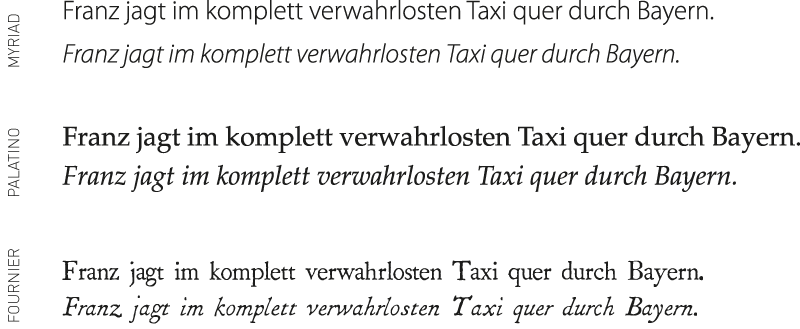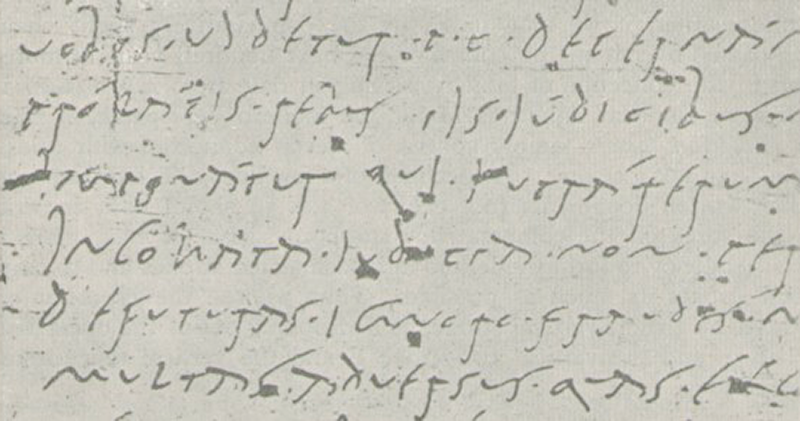
Die Bezeichnung „Kursive“ stammt aus dem Lateinischem ‚currere‘ = laufen, rennen und steht für schräg – meist nach rechts geneigte – laufende Schrift.
Die Geschichte der Typografie hängt unmittelbar zusammen mit der handgeschriebenen Schrift und Kalligrafie.
Die Form der Glyphen und der Duktus der Schrift – die sich aus der Form der Spitze des Schreibwerkzeugs und seiner Führung mit der Hand ergeben haben – haben später auch Einfluß auf die Form und das Aussehen der geschnitzten, gegossenen bzw. gedruckten Schrift. Während die Majuskeln (Großbuchstaben) von den römischen Inschriften (Antikes Rom, Trajanssäule) und die Minuskeln (Kleinbuchstaben, Gemeine) aus den Kleinbuchstaben des altgriechischen und römischen Alphabets abegeleitet werden, ist die Kursive eine Nachahmung der handgeschriebenen Schrift.
Die zahlreichen Abschriften der Majuskel-Schriften (Capitalis) führten zur Entstehung einer Majuskelkurssive (Capitalis Cursiva). Durch die ständige Veränderung der Form der Buchstaben entwickelte sich schliesslich die Minuskel mit den langen Endungen und Schleifen oben und unten (daher die Bezeichnung der Drei-Zonen-Schrift der „jüngeren römischen Kursive“).
Die Ausbreitung des Frankenreiches des Kaisers Karl des Großen führte zur Entstehung der „karolingischen Minuskel“ in der geraden und kursiven Ausprägung. Die Blütezeit erlebte die humanistische kursive Minuskel in der Renaissance. Sie setzte sich aus den Kleinbuchstaben der karolingischen Minuskel und den Großbuchstaben der Capitalis monumentalis. Einer der größten Förderer der humanistischen Minuskel war Niccoló Niccoli (1363–1437).
Die humanistische Minuskel war die Vorläuferin einer flüssig geschriebenen kursiven Form, welche ebenfalls unter dem Einfluß von Kalligraphen zur gepflegten Cancellaresca führte. Von der Mitte des 15. Jahrhunderts an entstanden in der päpstlichen Kanzlei die Sendeschreiben in vollendeter humanistischer Kursive, der Cancellaresca corsiva (oder littera da brevi) und der Cancellaresca formata, wogegen die päpstlichen Erlässe weiterhin in der littera da bolle, einer gebrochenen Schrift, geschrieben wurden. Die Cancellaresca verbreitete sich in Kürze über Europa und wurde zur beliebten Handschrift von Gelehrten und Künstlern (Caflisch M., Schriftanalysen, Bd. 1, 2003: 50).
Direkt aus der Cancellaresca formata entwickelt Francesco Griffo aus Bologna im Auftrag des venezianischen Druckers Aldus Manutius um 1501 eine aldinische Kursive mit der die Klassiker im Taschenbuchformat gedruckt werden sollen. Das Exklusiv-Recht für den alleinigen Gebrauch der Kursive, das Manutius von der Stadt erhalten hat, ist wirkungslos geblieben – binnen kürzester Zeit verbreitet sich diese Form in ganz Europa. In den Jahren 1524–27 bekommt die aldinische Kursive neue Konkurrenz: die römische Kursive von Ludovico degli Arrighi (Ludovico Vincentino).
Die Kursive existierte ursprünglich als eigenständige Schrift, bis sie ab dem 17. Jahrhundert als eine „Ergänzungsschrift“ der Antiqua-Schrift geschnitten wird. Der Franzose Philippe Grandjean legt der Schrift „Romains du Roi“ im Jahr 1702 eine Kursive bei. Später folgten dem Trend der königlichen Druckerei auch Pierre Simon Fournier (der ergänzt die kursiven Minuskeln um Serife) und Firmin Didot.
Anwendung der Kursive
Die Kursive wird im deutschsprachigen Raum für Auszeichnungen im Text eingesetzt.
Sie wird häufig für kurze Zitate oder Audrücke in fremder Sprache verwendet. Der Einsatz der Kursivschrift in den Versalien oder für den Titel sollte gut überlegt sein und hängt oft von der Schrift ab. Die Kursive verändert den Grauwert des Textes nicht. In kleinen Schriftgraden sollte die Kursivschrift immer spationiert werden.
„Echte“ Kursive vs. schräggestellter „Normal-Stil“
Für die Anwendung der Kursive in den digitalen Publikationen benötigt man neben der regulären Schrift eine zusätzliche kursive Schrift names „italic“ bzw. „oblique“. Dieser „italic“ Schnitt wird nicht elektronisch aus dem „normalen“ Schnitt durch die Schrägstellung optisch verzerrt, sondern von Typografen als Schnitt zusätzlich entworfen und im Programm über das Schriftmenü angewandt. Sehr deutlich sieht man den Unterschied beim Betrachten der Buchstaben „g“, „a“ und „f“.
Microsoft Word™ war früher von seinen künstlich erzeugten „Kursiv-Verzerrungen“ bekannt. Mittlerweile interpretieren die meisten Anwendungen den Knopf „Kursiv“
korrekt (vorausgesetzt, die Kursiv-Schnitte der Schrift sind installiert).